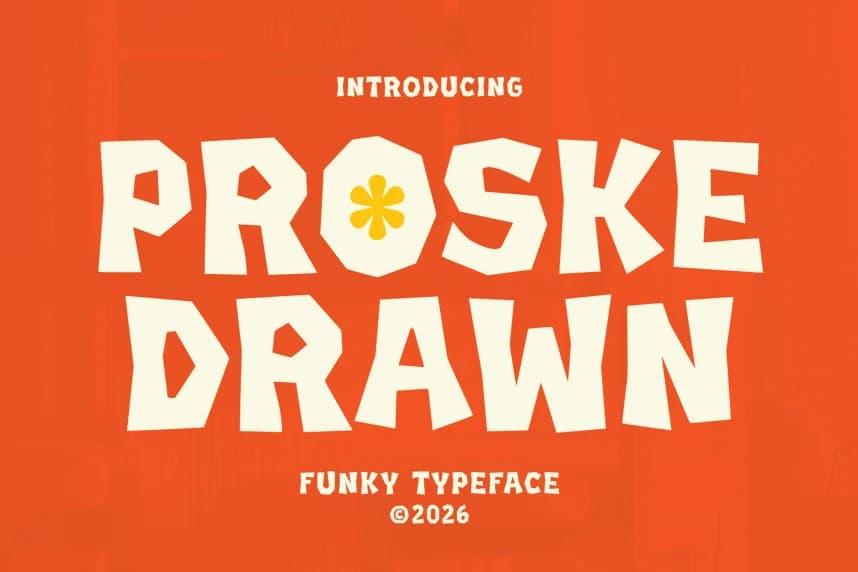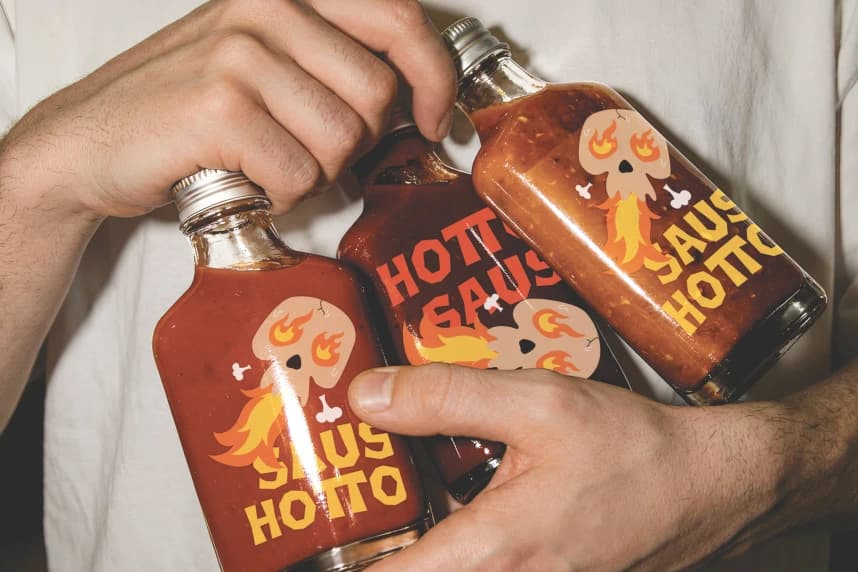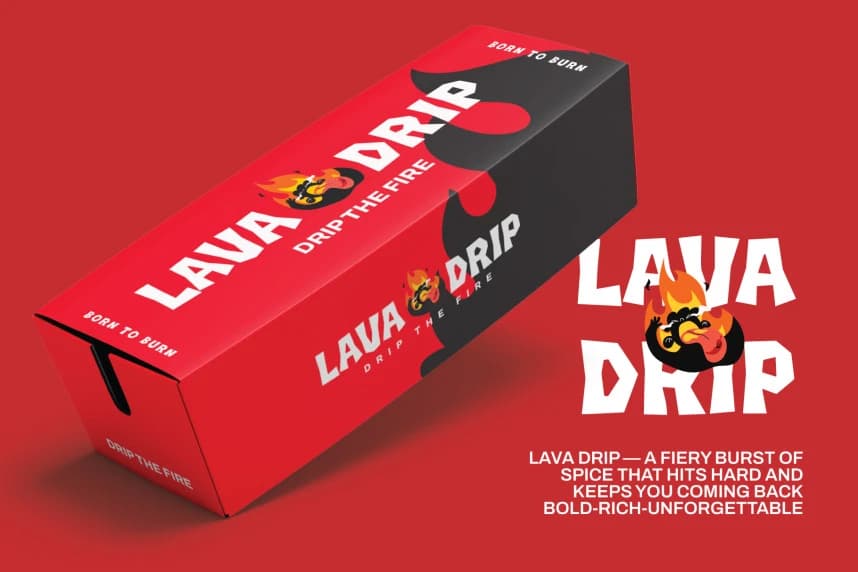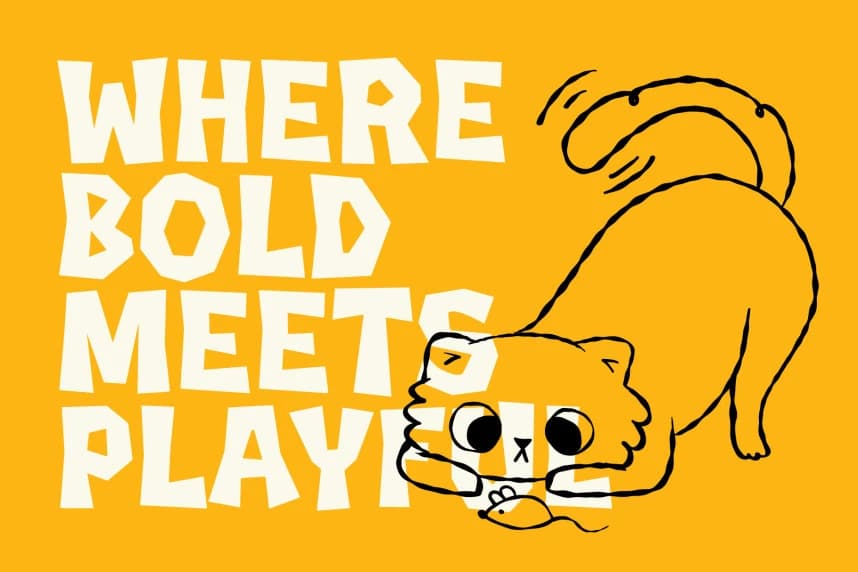
Proske Drawn – Funky Typeface
Proske Drawn – Funky Typeface. Proske, tasarımlarınıza enerji ve karakter katmak üzere tasarlanmış cesur ve oyuncu bir gösterişli yazı tipidir. Düzensiz şekillerine ve iri harf biçimlerine sahip bu yazı tipi, güçlü bir görsel etki sağlar ve izleyicinin dikkatini anında çeker.
Proske Drawn – Funky Typeface. Proske, tasarımlarınıza enerji ve karakter katması için tasarlanmış cesur ve eğlenceli bir gösterim fontudur. Düzensiz şekillerine ve kalın hatlı harf biçimlerine sahip bu yazı tipi, anında dikkat çeken güçlü bir görsel etki sunar.